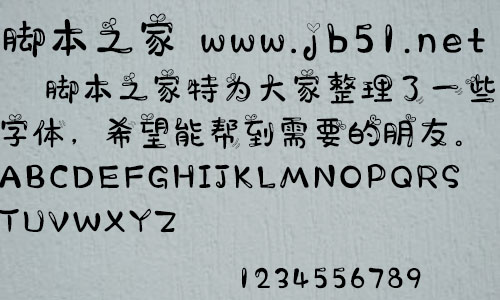
漢儀精靈之翼簡一款不錯的藝術(shù)字體,由漢儀字庫出品,字體筆觸適中,字形圓潤,以發(fā)芽的小草圖案作為點綴,具有很好的視覺感,適合應(yīng)用于藝術(shù)設(shè)計、平面宣傳設(shè)計、網(wǎng)頁設(shè)計,書法字帖等領(lǐng)域,需要的朋友可以前來本站下載。